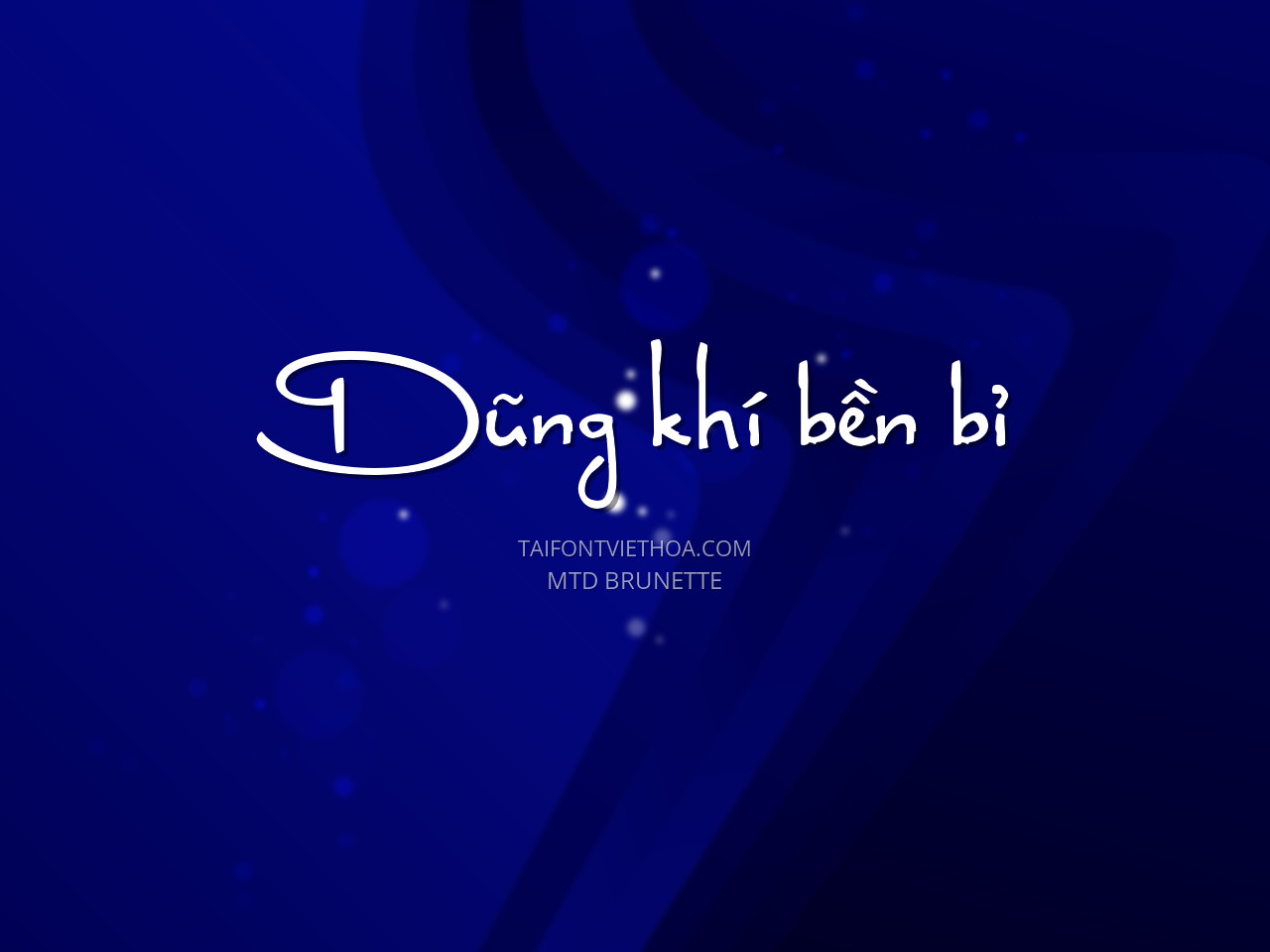
Giới thiệu về font Brunette – Thanh lịch, hiện đại và nữ tính
Brunette là một kiểu chữ viết tay hiện đại thuộc nhóm script font, được thiết kế với cảm hứng từ nét chữ phóng khoáng của những cuốn nhật ký cá nhân hoặc thư tay nghệ thuật. Font mang đến cảm giác mềm mại, nữ tính và thân thiện, rất phù hợp với các thiết kế mang yếu tố cảm xúc hoặc cần tạo sự kết nối nhẹ nhàng. Font thường được phát hành trên các nền tảng như Creative Market hoặc FontBundles, hỗ trợ hệ Latin mở rộng với hơn 60 ngôn ngữ phổ biến.
Phiên bản Việt hóa của Brunette do Mộc Hạthực hiện đã tối ưu đầy đủ bộ dấu tiếng Việt, giữ nguyên đường nét bay bổng của kiểu chữ gốc. Với thiết kế uyển chuyển, tinh tế và dễ ứng dụng trong nhiều ngữ cảnh, font Brunette đã được taifontviethoa.comchọn lọc và giới thiệu đến cộng đồng thiết kế như một công cụ lý tưởng cho các dự án đòi hỏi sự nữ tính, nghệ thuật và gần gũi.
Đặc điểm thiết kế mềm mại và các ứng dụng lý tưởng của font Brunette
Font Brunette có kết cấu chữ nghiêng nhẹ, nét chữ mềm, liền mạch như được viết bằng bút brush. Các ký tự được thiết kế mượt mà, bo tròn vừa phải và có độ tương phản nhẹ giữa các nét, giúp font giữ được cảm giác viết tay tự nhiên mà vẫn đảm bảo độ rõ ràng khi hiển thị. Font có sẵn các ligatures và glyphs thay thế (alternates), cho phép người dùng tuỳ biến bố cục chữ một cách nghệ thuật.
Font này phù hợp với nhiều thể loại thiết kế như: thiệp cưới, thư mời, logo mỹ phẩm, thiết kế thương hiệu nữ tính, blog cá nhân, trích dẫn truyền cảm hứng hoặc tiêu đề tạp chí phong cách sống. Ngành nghề phù hợp gồm: thời trang, mỹ phẩm, spa, tổ chức sự kiện, ảnh cưới – thiệp cưới, thương hiệu handmade hoặc bất kỳ sản phẩm nào cần thể hiện sự mềm mại và tinh tế trong thiết kế.